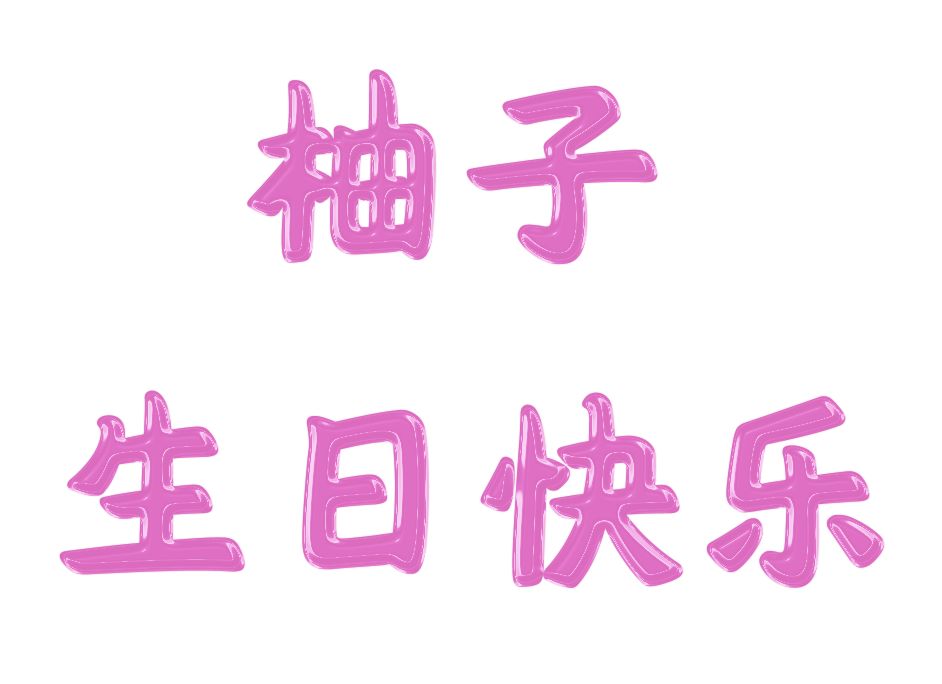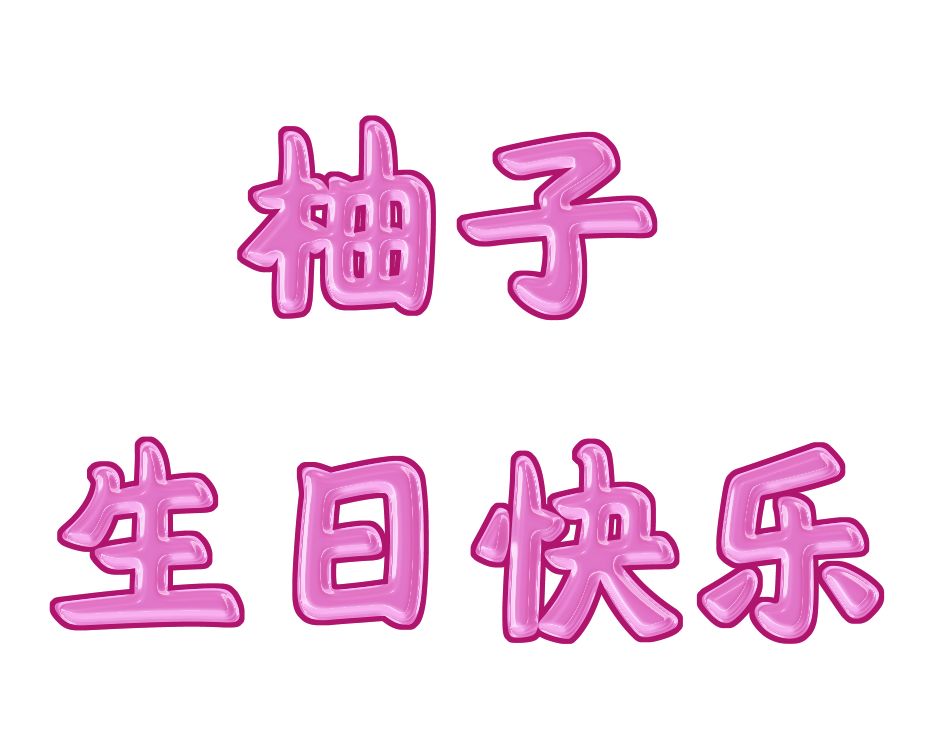
如何制作生日特效字体,烘托气氛的生日特效字,怎么做?
今天是柚子的生日,但不能去轰趴了,因为要上班,不过就算P一个,仪式感也是要的!
少女心的气球字
喜欢浪漫的双鱼座,一看到五颜六色的气球就hold不住了,如果再加入字形,要我嫁给你,都会跟着走了~
说做就做,新建一个2000x2000像素的文档,打上文字。
因为气球是圆圆的、鼓鼓的,所以我选了汉仪唐美人,在字由里激活变换~
接下来开始做图层样式,先斜面与浮雕。
光泽等高线可以根据效果,自己定~
接着是等高线,选预设的环形就好。
最后是投影,千万别默认,要调整~
做出来有点糖的感觉了。
第一层做好了,接着是第二层,复制图层,填充度改为0%,继续更改图层样式。
等高线也是自己调整,你应该会了。
是不是比糖又多了点光泽感~
坚持一下,还有最后一层,填充依然为0。
记得要把内发光加上,就ojbk了~
到这基本很像气球了,但还没完,还要压个小边边。
按住ctrl的同时,单击图层,得到选区。
再执行选择>修改>扩展,向外扩5像素。
新建一个图层,填充颜色,并至于最下层。
找一张纹理素材,放在新建的图层上方,再右键创建剪贴蒙版~
最后就是酱紫啦啦啦~
吃货的蛋糕字
过生日当然离不开蛋糕,我喜欢巧克力味的,那就做一个cake特效字,不过有点复杂,直接给你们一个PSD,当作礼物吧,字体是SAF~